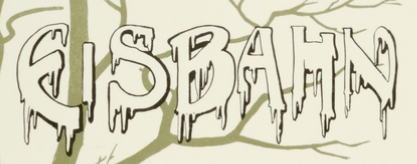
Suche "Die moderne Schrift" von Fr. A. Becker und F.Schweimanns, ca. 1903
Durch diese Datei bin ich überhaupt erst auf den Schweimanns gekommen, und nach dem darin enthaltenen Entwurf ensteht meine Version der Wodan.
Erst Dein Link hat mir aber die Erleuchtung gebracht, daß ich vielleicht mal beim Klingspormuseum anfragen sollte, wo die Ihre Scans hergenommen haben...Viel Dank also für die Eingabe!
Dank Bertels link habe ich Bilder der Tafeln 31-35 und 39-54. Um den Rest habe ich mal beim Klingspor-Museum angefragt. Mal sehen, ob daraus was wird.
Es wurde nichts. www.klingspor-museum.de hat nichts mit dem Klingspor-Museum in Offenbach zu tun. Deren webadresse lautet nämlich www.klingspormuseum.de. Man kann sich ja irren :-?
Übrigens gibt sich die Website mit dem Bindestrich als durchaus seriöser Internetauftritt des Museums aus, mit Öffnungszeiten und so. Erst beim zweiten Lesen fielen mir die Links auf die "offizielle website" und das wiederholte Wort "ehrenamtlich" auf.
Ist es auch – aber nur, wenn Du über die Homepage in die Website einsteigst. Nicht aber wenn Google oder der oben eingestellte Link Dich direkt auf eine der vielen PDF Dateien bringt.
Übrigens habe ich inzwischen erfahren, daß es sich hier nicht etwa um eine Büberei handelt:  in grauer Vorzeit hat sich jemand aus Begeisterung bereit erklärt, für das Museum, und mit dessen Zustimmung, eine Website zu gestalten.
Die (überaus hilfreichen) Inhalte, insbesondere die vielen PDF-Datein zu verschiedenen Schriftgestaltern (sogar zu mir!)  haben aber nichts mit dem Klingspor-Museum oder seinen Beständen zu tun, und das führt anscheinend immer wieder zu Missverständnissen.
Genau. Die zwei Herren, die hinter diesen PDF-Dateien stehen, sind wirklich topp. Die Information ist unersetzbar. Ich finde die Information auf den Seiten wirklich wichtig. Klar, es ist ärgerlich, wenn man mehr über eine bestimmte Person oder eine bestimmte Schrift herausfinden möchte, und man in den PDFs nicht viel Information steht. Aber für die historischen Personen bzw. Schriften kann ich sagen … wenn es nicht mehr in den PDFs zu sehen gibt, ist das, weil es zu diesen Personen oder Schriften wirklich wenig übrig zu finden ist. Höchstens findet man mehr über denen aus, wenn man in den Fachperiodika der Zeit durch liest. Aber diese Erkenntnisse gewinnt man eher über Zufall. Das Textkorpus aus dieser Zeit ist größtenteils noch undigitalisiert, zumindest was das Schriftgießereigewerbe angeht.
Ich kenne einen der Herren (Hans Reichardt) persönlich. Dieser Herr hat ein immenses Wissen was sowohl den Bleisatz als auch die Digitalisierung der Schriften für die diversen DTP-Systeme angeht. So hat er uns ausführliche erklärt, warum die digitale Reporter so aussieht, wie wir sie heute vom Computer her kennen und nicht mehr viel mit der Reporter im Bleisatz zu tun hat: „Damals waren Rechenleistung und vor allem Speicherkapazität stark begrenzt, also hat man vieles/alles weggelassen, was zu aufwändig war. Bei der Reporter die ganzen Details, die den Pinselstrich-Charakter erst ausmachen."
Selbst in Zeiten von OTF und SVG-Fonts hat sich niemand dran gemacht diesen Missstand zu beheben und/oder dazu noch die ganzen tollen Ligaturen und Alternativbuchstaben mit unterzubringen.